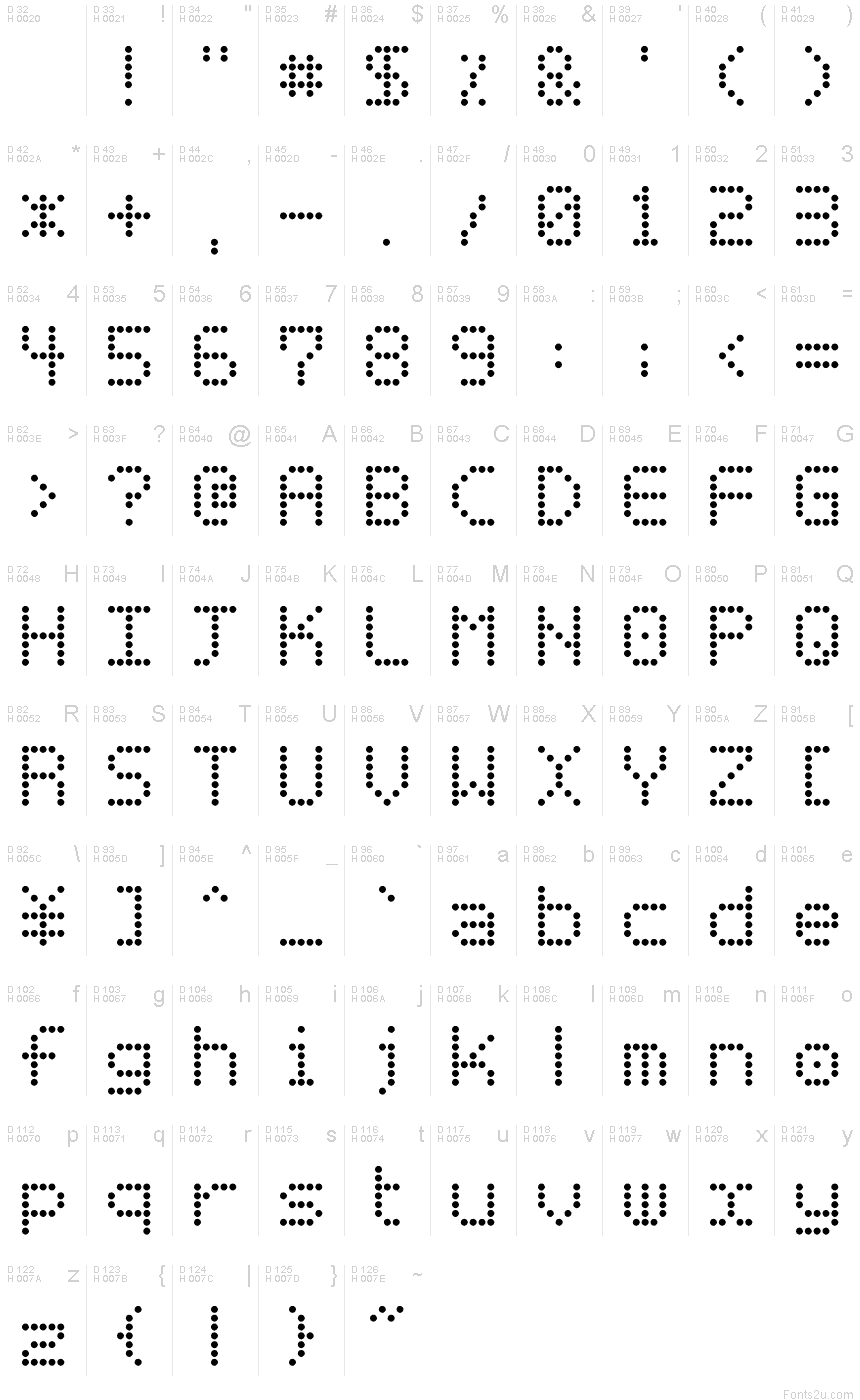
Basicdots di Masachika Yamasaki è un carattere digitale display gratuito che trasforma ogni parola in una griglia di punti nitidi e uniformemente spaziati, come un pannello LED retro bloccato sullo schermo. I moduli arrotondati offrono un aspetto tattile e leggermente giocoso, ma la spaziatura è abbastanza stretta da mantenere i messaggi compatti e leggibili. Alle dimensioni più grandi, il motivo diventa quasi architettonico, conferendo ai titoli un'atmosfera da insegna luminosa strutturata, senza bisogno di effetti aggiuntivi.
Con Basicdots, puoi dare istantaneamente a poster, flyer, titoli di fantascienza, interfacce di gioco, copertine di album o segnaletica digitale quel bagliore nostalgico dell'hardware d'altri tempi. Questo font gratuito funziona meglio se mantieni il testo breve e in grassetto, abbinandolo a un semplice sans-serif geometrico per il corpo del testo. Provalo in grandi dimensioni su sfondi scuri per imitare i pannelli a matrice di punti, oppure invertilo su bianco per un tocco tecnico e pulito.